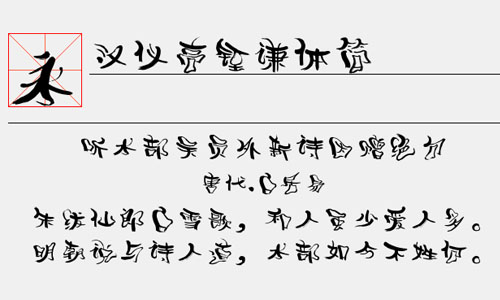
漢儀高铚謙體簡字體是一款很優(yōu)秀好用的用于藝術(shù)設(shè)計(jì)方面的繁體字體。這款字體笨拙有點(diǎn)抽象,但看起來非常漂亮,整體效果非常均勻,字體完整??蓮V泛用于藝術(shù)設(shè)計(jì)和新聞媒體,在宣傳海報(bào),ppt,電影和電視制作以及內(nèi)容詞方面。歡迎喜歡漢儀高铚謙字體的朋友前來下載使用。